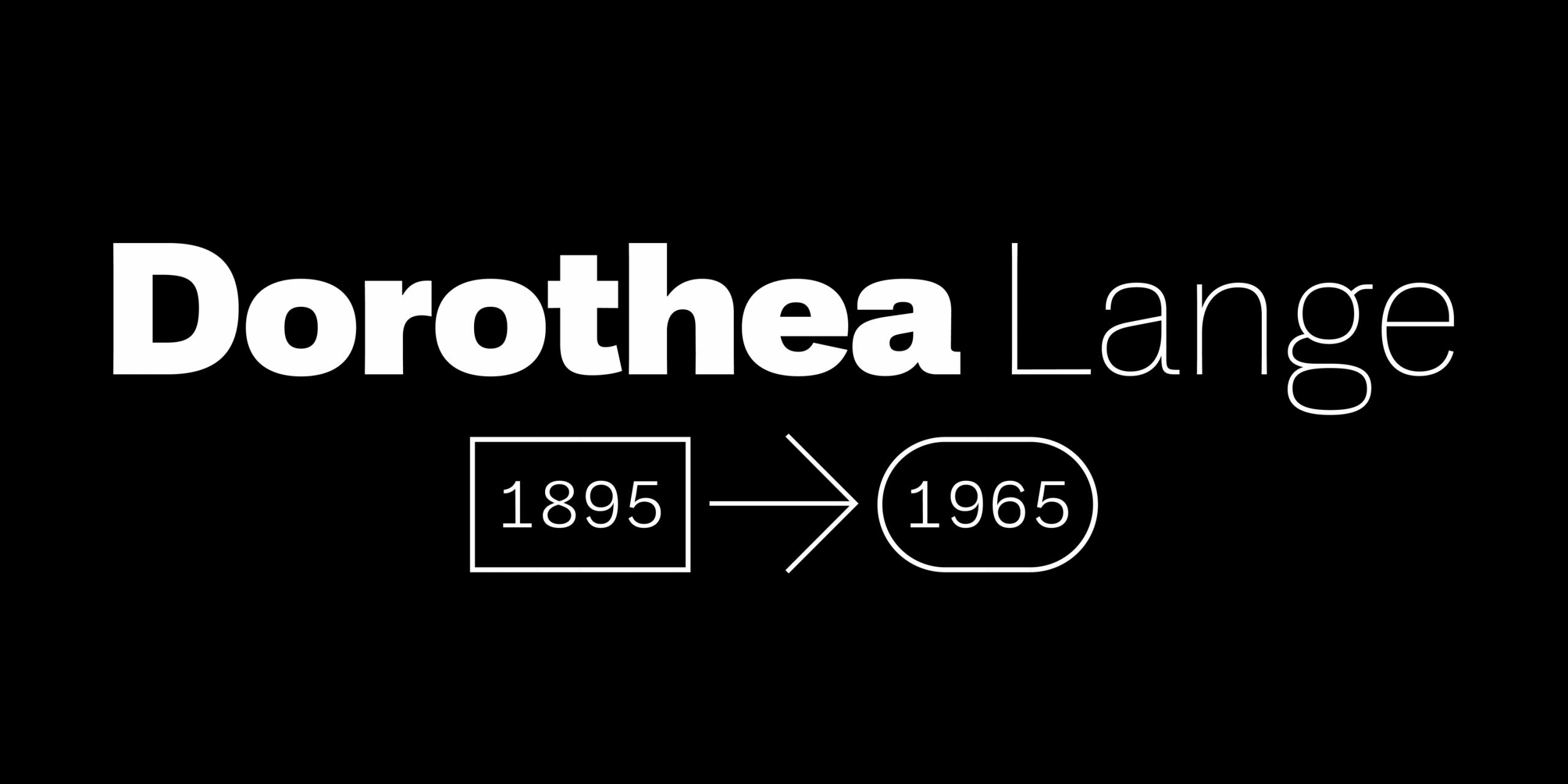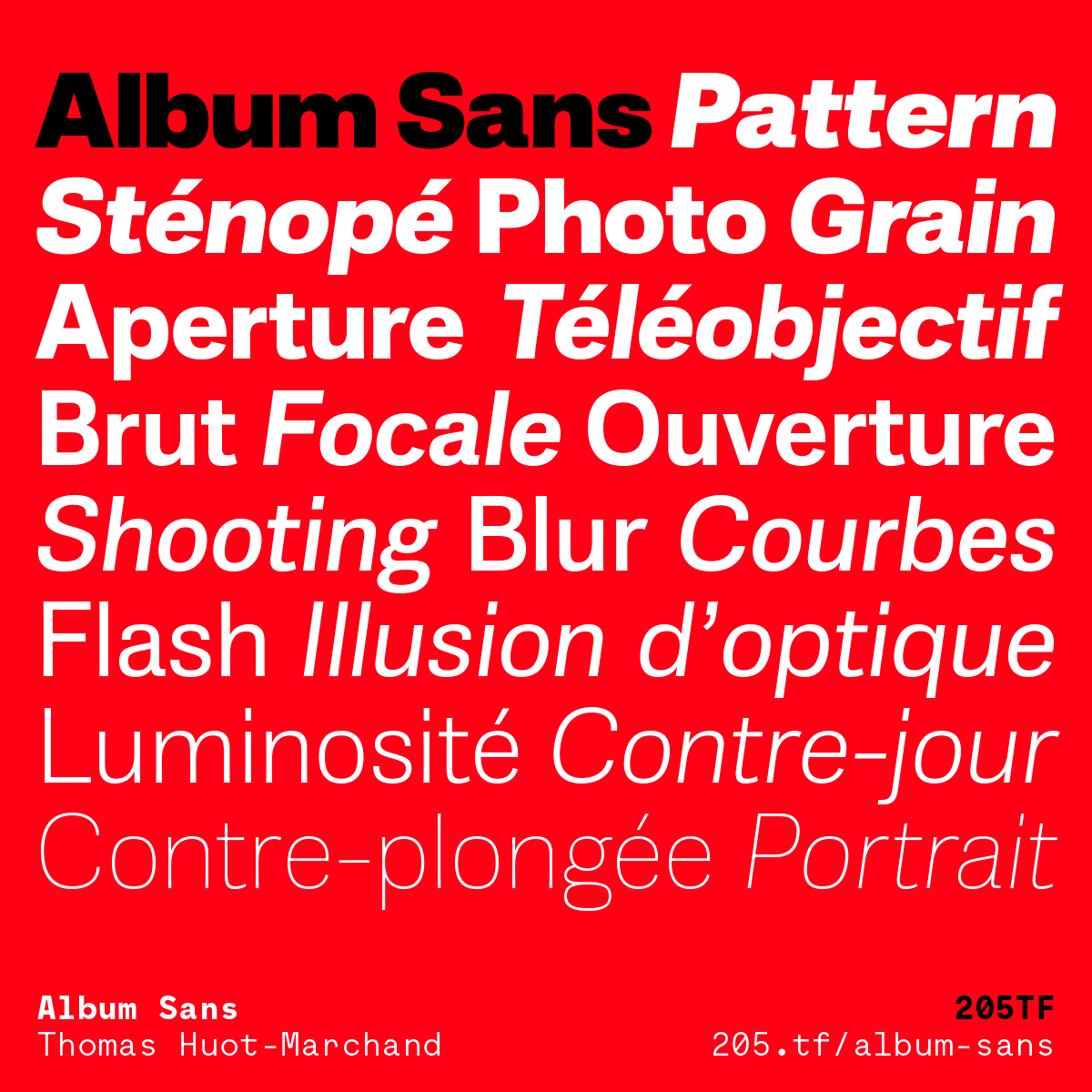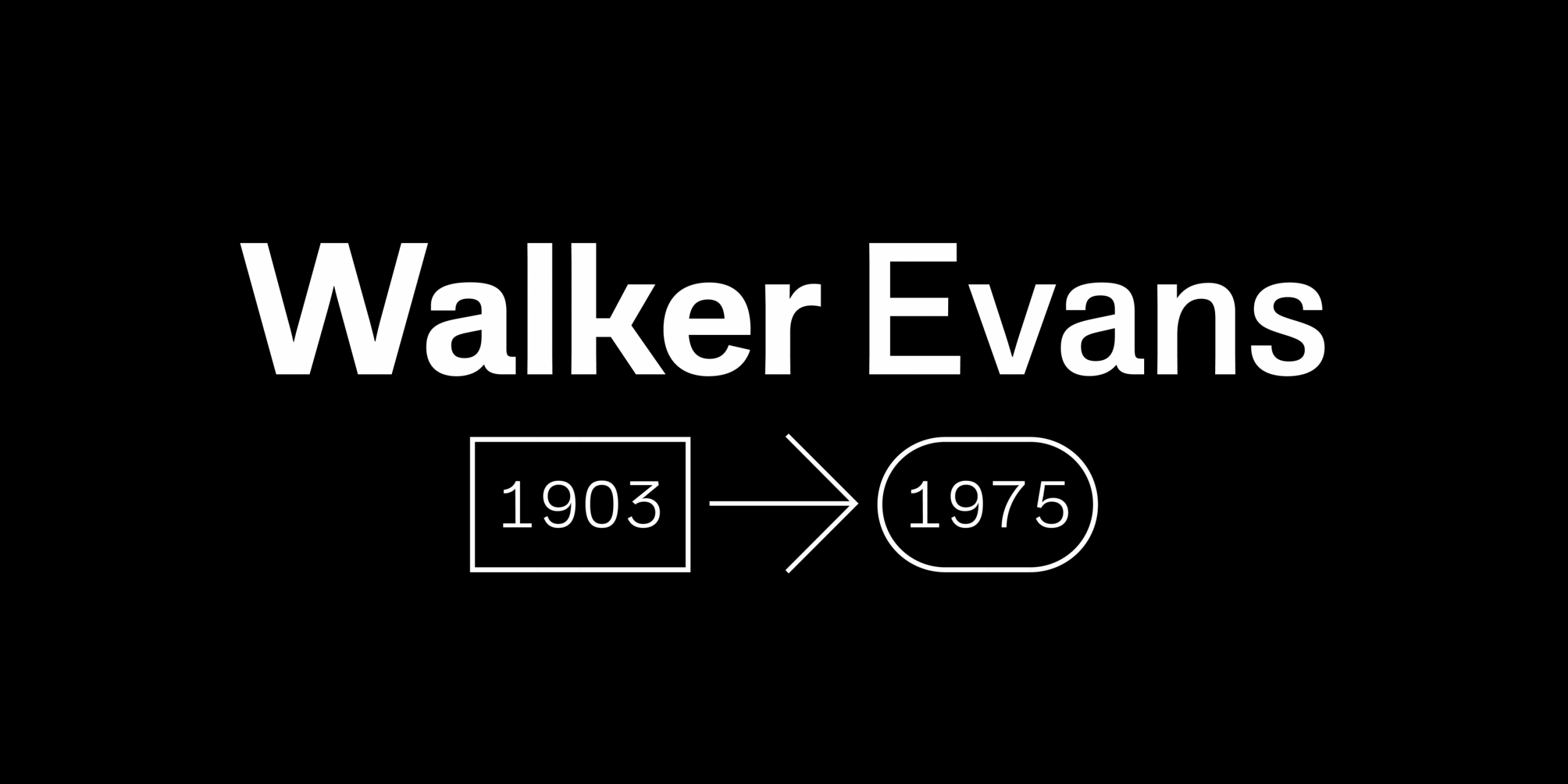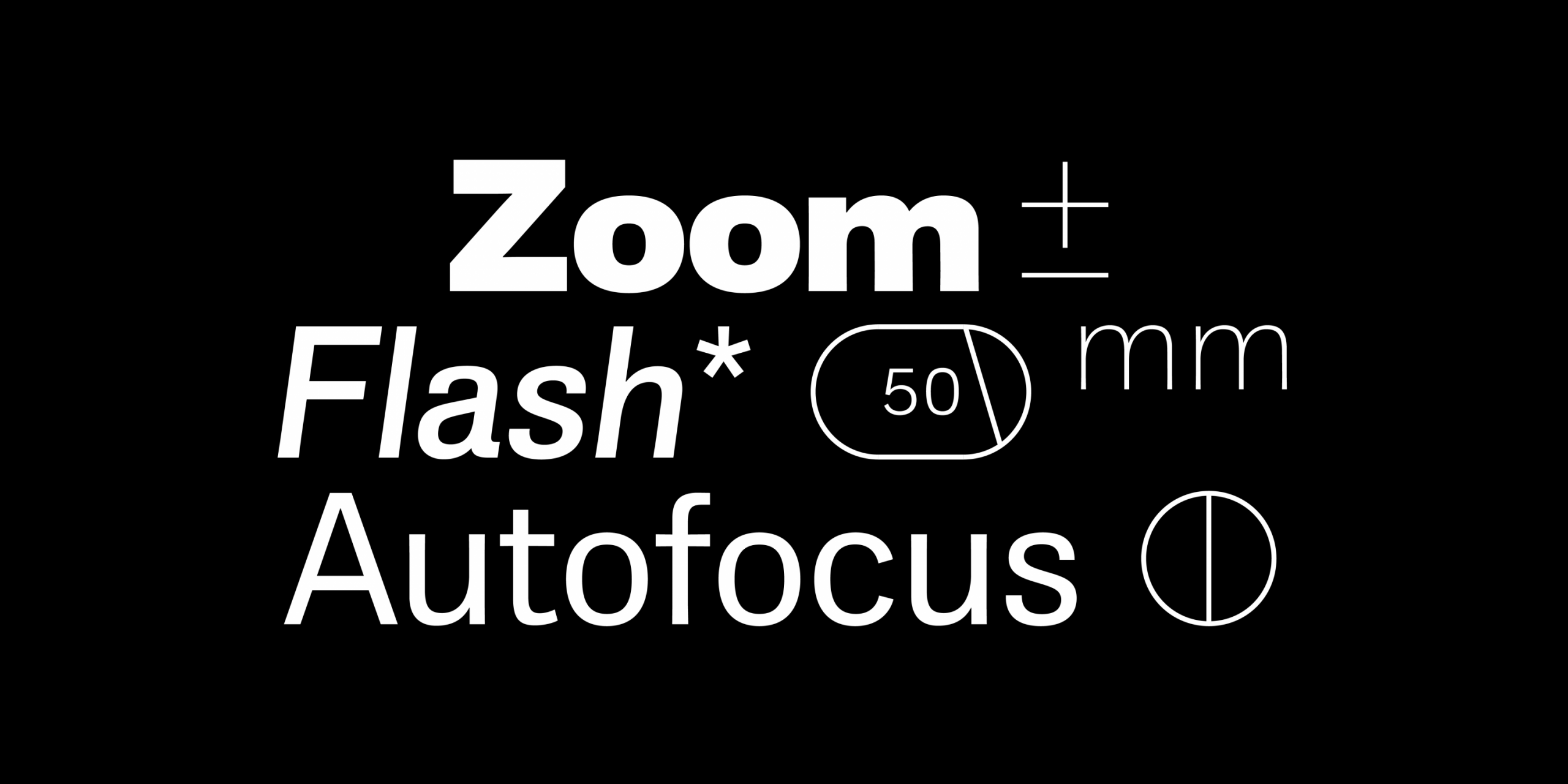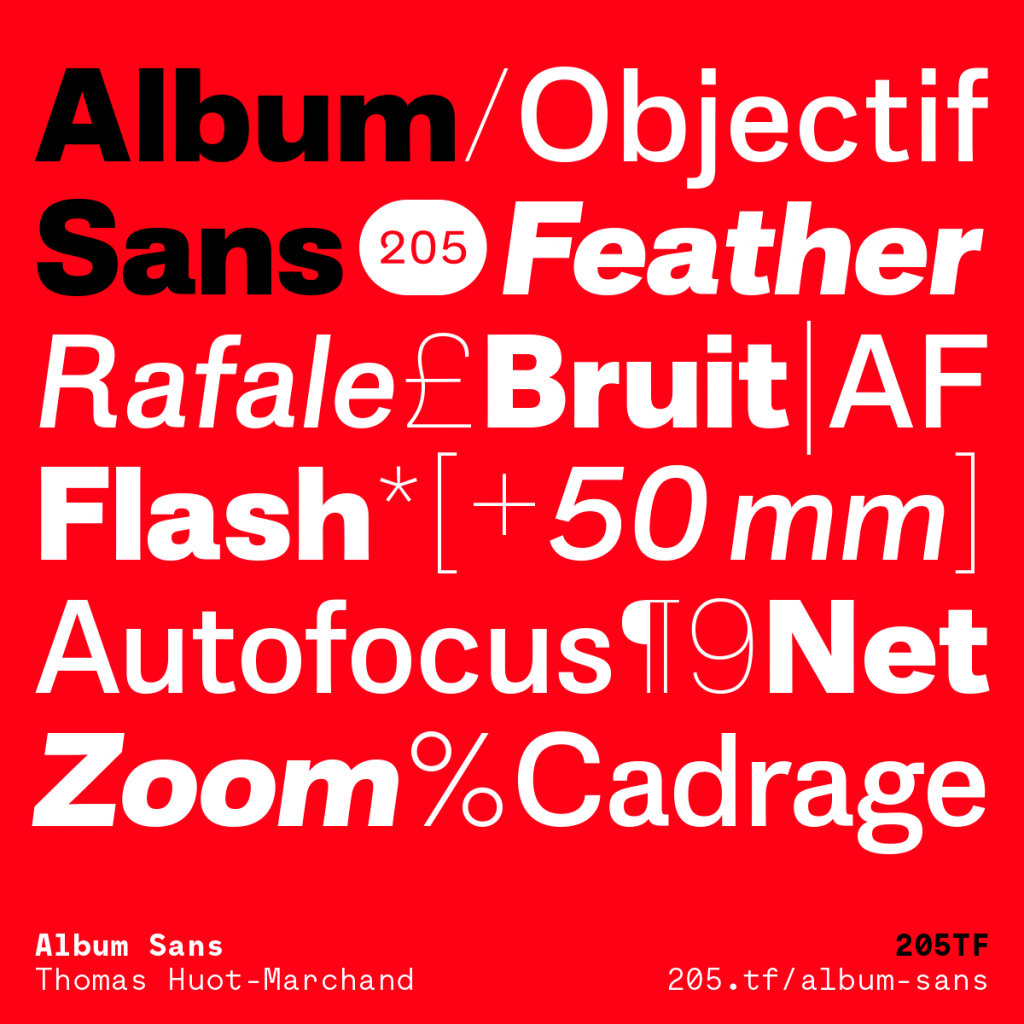
Album Sans
• Schrift-Name Album Sans
• Design, Entwicklung Thomas Huot-Marchand
• Mastering Thomas Huot-Marchand
• Version 1.1
• Veröffentlicht 2021
• Schriftschnitte  16
• Font Foundry 205TF
Die Wörter Zoom, Flash und Autofocus, gesetzt in der Schrift Album Sans, umgeben von einigen Zeichen zeigen den Character der Schrift.
Schriftmuster für die Schrift Album Sans von Thomas Huot-Marchand. Man sieht den Namen Walker Evans und darunter Jahreszahlen, gesetzt in Rahmen, verbunden durch einen Pfeil.
Schriftmuster für die Schrift Album Sans von Thomas Huot-Marchand. Man sieht den Namen Dorothea Lange, darunter Jahreszahlen in Rahmen, verbunden durch einen Pfeil.
The Font
Justus Erich Walbaum (1768–1837), a confectioner by trade, carved his own cake molds. A highly skilled craftsman, he developed a career as a punch-cutter and eventually purchased Ernst Wilhelm Kirschner’s type foundry. Considered one of the most important designers of his time, he created both Gothic and Antiqua typefaces, the latter of which were similar to those of Didot and Bodoni. However, Walbaum’s designs were unique, and some argue that they contain the origins of the Grotesques that followed.
In 2010, Thomas Huot-Marchand and SPMillot were commissioned to design the typographic identity of the Musée d’Orsay (Paris), which had been based on Berthold Walbaum since the museum’s inception. They proposed adding distant “cousins” in later typographic styles: a bold grotesque and a thin slab serif, though these typefaces ultimately remained unused.
Ten years after, Thomas Huot-Marchand decided to redesign them while developing an extended family. Album is a subtraction of Walbaum: Album Sans has no serifs, and Album Slab has no contrast. Its silhouette retains some memory of Walbaum’s particular proportions and slightly flattened curves.
Album Sans offers a new interpretation of grotesques with an extended range of weights. The horizontal terminations of the R and the a, the binocular g, the junction of the k, along with the singular design of the numerals, distinguish it from more common forms, as does the unique design of the numerals.
Die Schrift
Justus Erich Walbaum (1768–1837), war Konditor, schnitzte seine eigenen Kuchenformen. Als äußerst geschickter Handwerker wurde er anschließend Stempelschneider und erwarb schließlich die Schriftgießerei von Ernst Wilhelm Kirschner. Walbaum gilt als einer der bedeutendsten Gestalter seiner Zeit und schuf sowohl gotische als auch Antiqua-Schriften, wobei letztere denen von Didot und Bodoni ähnelten. Walbaums Entwürfe waren einzigartig und man kann der Ansicht sein, dass sie den Ursprung der späteren Grotesken-Schriften bilden.
2010 wurden Thomas Huot-Marchand und SPMillot beauftragt, die typogra­fische Identität des Musée d’Orsay (Paris) zu gestalten. Diese basierte seit der Gründung des Museums auf der Schrift Berthold Walbaum. Sie schlugen vor, entfernte Verwandte aus späteren typogra­fischen Stilen hinzuzufügen: eine fette Groteskschrift und eine schmale Slab-Serif-Schrift, letztendlich blieben diese Schriftarten ungenutzt.
Zehn Jahre später beschloss Thomas Huot-Marchand, sie neu zu gestalten und gleichzeitig eine erweiterte Schriftfamilie zu entwickeln. Album ist eine Reduktion von Walbaum: Album Sans hat keine Serifen, und Album Slab weist keinen Kontrast auf. Ihre Silhouette erinnert an die besonderen Proportionen und leicht abgeflachten Kurven von Walbaum.
Album Sans bietet eine neue Interpretation der Grotesk-Schrift mit einer erweiterten Auswahl an Schriftstärken. Die horizontalen Abschlüsse des R und des a, das binokulare g, die Verbindung des k sowie das einzigartige Design der Ziffern unterscheiden sie von gängigeren Formen.
The Font Designer
Thomas Huot-Marchand (1977) lives and works in Besançon, France. After graduating in Besançon school of fine arts in 2001, he joined the Atelier national de recherche typographique (ANRT) where he studied typeface design (with Peter Keller, Jean Widmer, Hans Jurg Hunziker, André Baldinger & Philippe Millot). He designed Minuscule, awarded by the Type Directors Club in 2005, and later considered as one of the „ten typefaces of the decade“ (Paul Shaw, Imprint). In 2006, he spent one year as resident fellow at the Académie de France à Rome – Villa Medici. He teached graphic and typographic design in Besançon and in Amiens from 2002 to 2012. Since 2012, he’s the director of the Atelier national de recherche typographique (https://anrt-nancy.fr/fr) a post-graduate research course based in Nancy (www.anrt-nancy.fr). He published in 2016 the catalogue ANRT Archives, 1985-2006. Typographer in residency at the Hoffmitz-Milken Center for Typography (H_M_C_T) in Pasadena in 2019. Since 2017, his typefaces Minuscule, Minérale, Garaje (all awarded by the TDC) and Album are distributed by 205TF (www.205.tf)
Der Schriftdesigner
Thomas Huot-Marchand (1977) lebt und arbeitet in Besançon, Frankreich. Nach seinem Abschluss an der Kunsthochschule in Besançon im Jahr 2001 trat er dem Atelier national de recherche typographique (ANRT) bei, wo er Schriftgestaltung studierte (bei Peter Keller, Jean Widmer, Hans Jurg Hunziker, André Baldinger und Philippe Millot). Er entwarf die Schrift Minuscule, die 2005 vom Type Directors Club ausgezeichnet und später als eine der „zehn Schriften des Jahrzehnts“ (Paul Shaw, Imprint) gewürdigt wurde. Im Jahr 2006 verbrachte er ein Jahr als Stipendiat an der Académie de France à Rome – Villa Medici. Von 2002 bis 2012 unterrichtete er Grafik- und Typografiedesign in Besançon und in Amiens. Seit 2012 ist er Direktor des Atelier national de recherche typographique (https://anrt-nancy.fr/fr), eines postgradualen Forschungsstudiengangs mit Sitz in Nancy (www.anrt-nancy.fr). Im Jahr 2016 veröffentlichte er den Katalog ANRT Archives, 1985–2006. 2019 war er als Typograf im Hoffmitz-Milken Center for Typography (H_M_C_T) in Pasadena zu Gast. Seit 2017 werden seine Schriftarten Minuscule, Minérale, Garaje (alle vom TDC ausgezeichnet) und Album von 205TF (www.205.tf) vertrieben.
Schriftmuster für die Schrift Album Sans von Thomas Huot-Marchand. Gezeigt werden auf hellrotem Grund die Wörter Album Sans in schwarz und weitere Wörter, Zahlen und Zeichen in weiss.
205TF ist eine Schriftgießerei mit menschlicher Dimension. Neben dem Vertrieb ihrer Arbeiten unterstützt sie Schriftgestalter, indem sie ihnen ein breiteres Publikum und größere Anerkennung verschafft. Außerdem hilft sie ihnen bei der Entwicklung ambitionierter Projekte, wie variable Schriftarten, erweiterte Glyphensätze und Mastering.